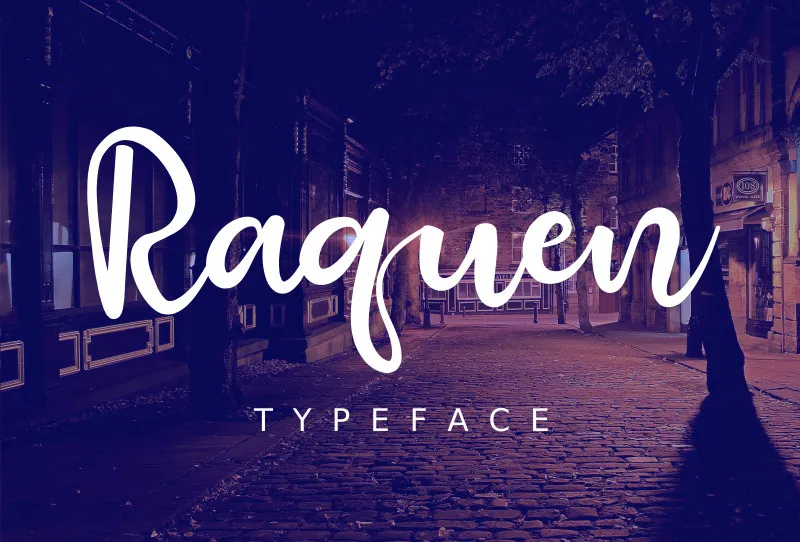
Raquen Script Font – Download Grátis
A Raquen Script Font é uma escolha perfeita para arquitetar design vintage no seu projeto. Esta elegante e simples font pode ser usada em diversas aplicações, como textos de citação, capas de livros, logomarcas, cartões de convite de casamento, cartazes e muito mais. Desenvolvida com um olhar para o estilo vintage moderno, a Raquen Script oferece uma aparência limpa e elegante que certamente enriquecerá qualquer projeto. Seu designer, dilbadil, criou um resultado inspirador e autêntico, perfeito para quem procura um toque de sofisticação no seu trabalho gráfico.